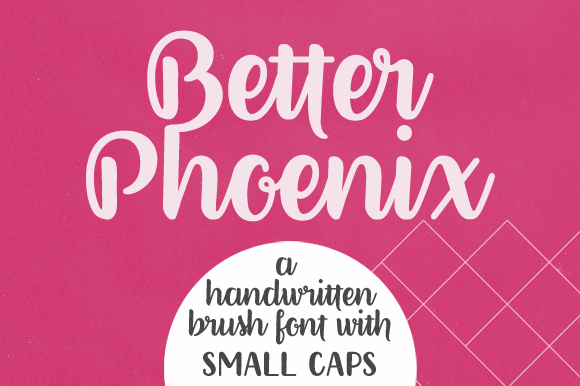
“Bem Phoenix” é uma fonte polida feita à mão com 400+ sinais, ideal para quem busca uma fonte única e elegante que combina bem tanto em textos formais quanto em design gráfico moderno. Seu designer, Hamilton, trouxe uma paleta de estilo e personalidade a essa fonte, dando-lhe um toque suave mas poderoso. A sua natureza fluente e fluida é perfeita para estilos de letra script ou para aplicação em desenhos digitais, tornando-a uma escolha inteligente para designers que valorizam tanto o bom design quanto a praticidade da tecnologia digital. Embora “Better Phoenix” seja mais conhecida por sua versão Script, ela ainda oferece um conjunto amplo e consistente de caracteres, o que significa que pode ser usada em textos significativos ou gráficos complexos sem perder a essência única que a torna tão interessante. É uma fonte perfeita para aqueles desejando trazer mais vida à escrita em seu projeto. Com “Better Phoenix”, designers e criadores de conteúdo não têm medo de expressar suas ideias de maneira autêntica e profissional, seja ela na forma de um texto estiloso ou no design de um logotipo sofisticado.